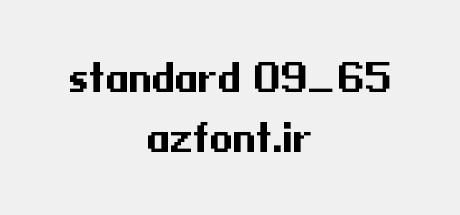
فونت زیبای رایگان standard 09_65
قلم زیبای standard 09_65 از سری قلم های بسیار زیبا برای تایپوگرافی و لوگو تایپ می باشد.این قلم در وزن Regular و توسط Regenerated by Nadim Shaikli طراحی و منتشر شده است.